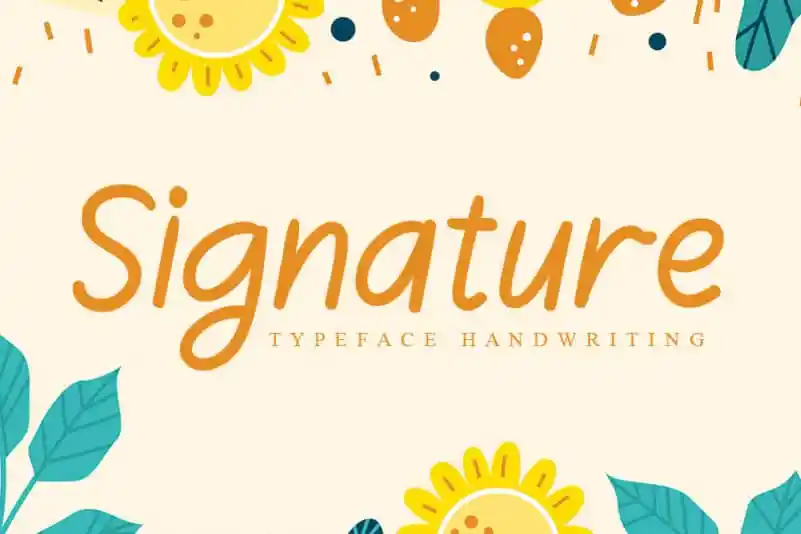
A Signature Handwritten Font é uma escolha perfeita para quem procura uma fonte de escrita feita à mão que combine a simplicidade com um toque encantador e amigável. Seu estilo natural e único faz dela uma opção ideal para um amplo leque de designs, desde logotipos até materiais de publicação. A qualidade única desta fonte não apenas adiciona um charme distintivo às criações digitais, mas também garantirá que sua marca fique marcada na memória dos consumidores. Ideal tanto para designers que procuram uma personalidade mais suave e reconfortante quanto para aqueles que valorizam a autenticidade nas suas ideias e produtos. Não hesite em experimentar esta fonte de escrita feita à mão, ela definitivamente fará sua marca.